创造“o”和“n”
设计字体有很多种方法。解构涉及的大规模的进程,以快速开始并为整个字体的字符的价值提供坚实的基础。这样做是有益的。达到这个目的的一个受欢迎的有价值的方法是首先设计“o”和“n”,在定下形式、间距和平衡的必要元素,然后再将它们合在一起形成其他字符。创建小写的“o”和“n”字符可以提供给我们一些基本的形式和结构,可以支撑所有其他的需要的字符。
尽管设计“o”可能看起来是十分容易的事情,但是所有在“什么是字体?”一章中提到的字符都开始起作用。你对每个字符所做出的选择应该是深思熟虑的。
下垂和上突
光学效果影响字体设计的一种方式是曲线和直的边在眼睛里是如何出现。 比如说,如果要曲线和直边看起来正确地在基线上对齐,那么实际上曲线必须放在基线以下一点点,这就产生了下突。为了看起来放置在基线上而压低到基线以下的字符的那部分称作下垂 –如下演示。没有下垂,基线附近有曲线的字符将会看起来没有在文本的线上对齐。
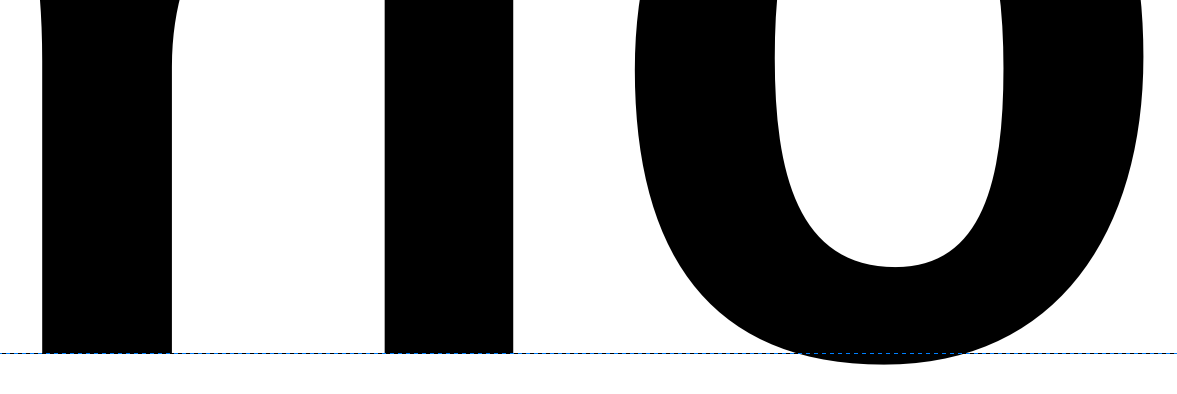
类似于下突,提供 x 高度和大写高度的对齐错觉需要一部分区域上突(如下)。
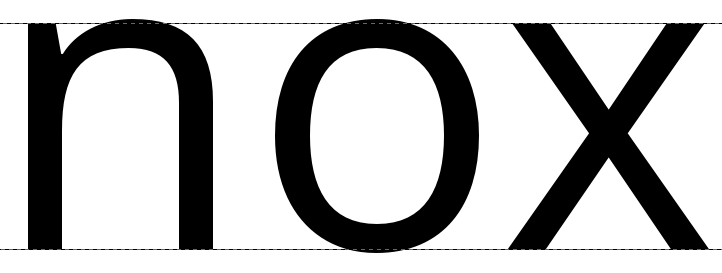
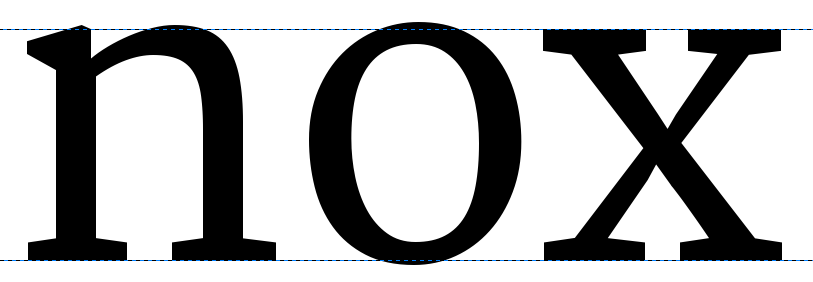
设计小写“o”
设计“o”不仅仅是字母中黑色部分的问题。“o”提供了非常基本的弧(bowl)的粗细和形状,白色部分–或对立面–提供了字体其他部分使用的尺寸和形状。一般说来,我们也可以在其他字符中看到“o”中的圆形。这些字符包括 b,c,d,e,p 和 q,这些形式也会影响字体中其他字符的曲线的形状和形式,比如 O,C,D 和 Q。
此外,“o”中的白色部分应该在设计字体间距的时候利用起来;“o”也会设定字体中其他字形间使用的间距。这两个值之间关联很大,因此基本上你也需要设计你的“o”两旁的空白数量。作为一般原则,除了斜体或者意大利斜体,其他字体的“o”左右两边的间距是相同,“o”字符的字符串的空白间距应该与“o”内的空白间距相平衡。
我们已经接触了很多间距和度量值,所以即使在这一较早阶段,你也可能希望看一下“间距,度量值和紧缩”一章,涵盖了字体间距的基本含意。这样将会使你做出间距很好的字符“o”,这样对你设计“n”也有帮助。
设计小写的“n”
一旦你可以对你的小写字符“o”的形式和间距感到高兴,就像展示的示例字符串那样,那么下一步就是创造形状合适、平衡、间距良好的小写字母“n”,这样你就可以将其插入“o”的字符串。
如果我们观察“n”的解刨,我们可以将其分割成 2 或 3 个组成部分,包括一个茎和一条曲线。
这种方式可以在我们的字符集增长的时候,给你形成字符时与其他字符保持平衡和谐的捷径。看下面的例子“n”;他被分为两部分。分开的组件合在一起就形成了一个“n”,但是同样的组件在稍后形成其他字符的时候可以再次使用;比如左边的“n”的茎可以在形成其他所有小写字母的茎的时候使用。
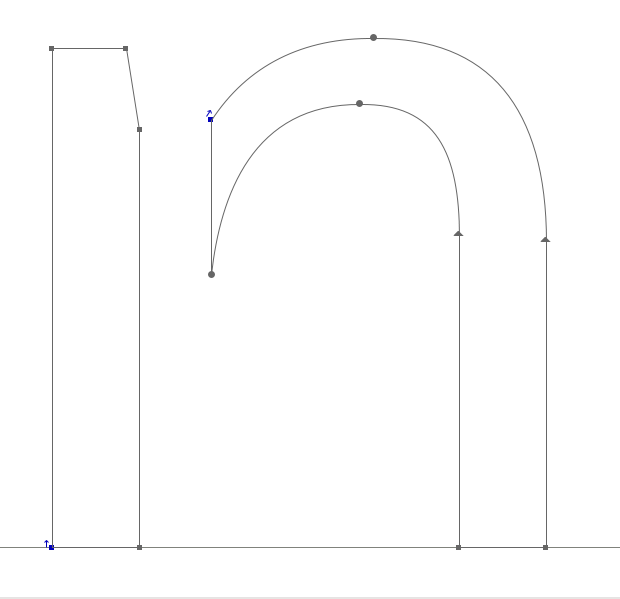
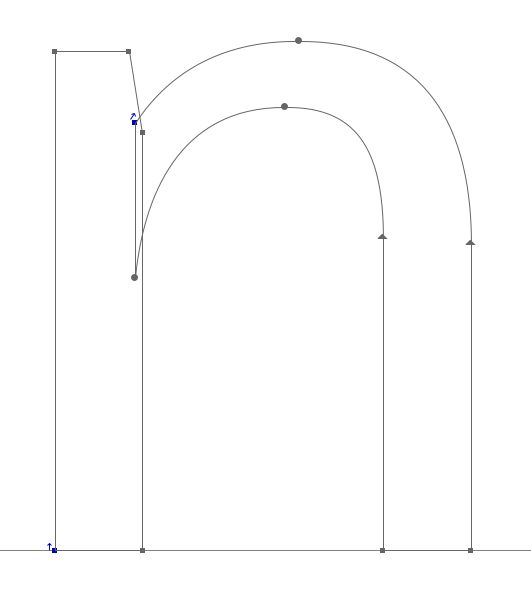
你可以再次快进到间距和度量值的章节,字符“n”的设计应该跟上调整字符“n”和“o”间距的进程。
现在利用你所使用过的方法来创造一个“n”和一个“o”字符,你已经准备好扩大小写字符集。“o”和“n”的茎和曲线组件为你形成其他字符指明道路。如果我们学习下面的来自Open Sans的字符,我们可以看到各个字符的正式面貌以及他们如何重复出现,通过一些调整形成新的字体的组件。